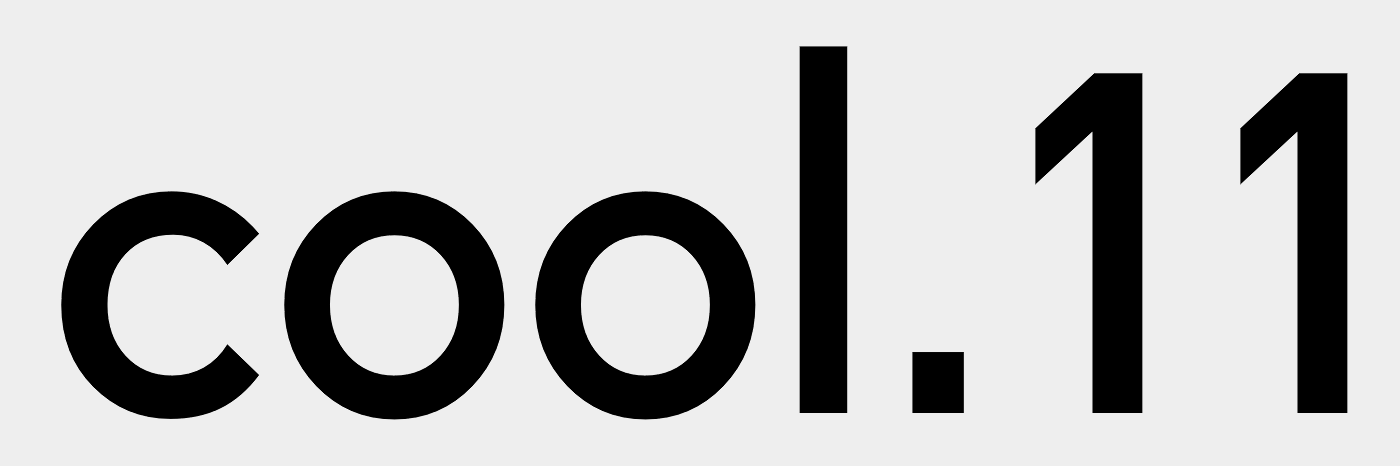
Welche Schrift kann das sein? (Cool.11)
Hi, Robert, danke für die rasche Reaktion. Das hat vor rund 15 Jahren ein Grafiker gemacht, es gibt sonst nichts!
Hi, das würden wir gerne - aber das sind wir. Den Grafiker gibt's nicht mehr, deshalb unsere Frage. LG Hans
Also ich bin ja nun am wenigsten Experte in der Schriftenerkennung, würde jetzt aber mal so ganz naiv auf eine Avant Garde mit – zwecks besserer Ziffernerkennbarkeit im Logo – hingedengelten Einsen tippen. :-?
Die 1 sieht aus, als hätte jemand an der Drescher Grotesk gespielt.
Das ist ja auch schon mal eine Info. Es müsste also eine Schrift sein, die mindestens schon genauso viele Jahre auf dem Buckel hat. Damit scheiden die ganzen neuen Geometrischen schon mal aus und @Þorsten liegt vielleicht gar nicht so falsch. ;-)